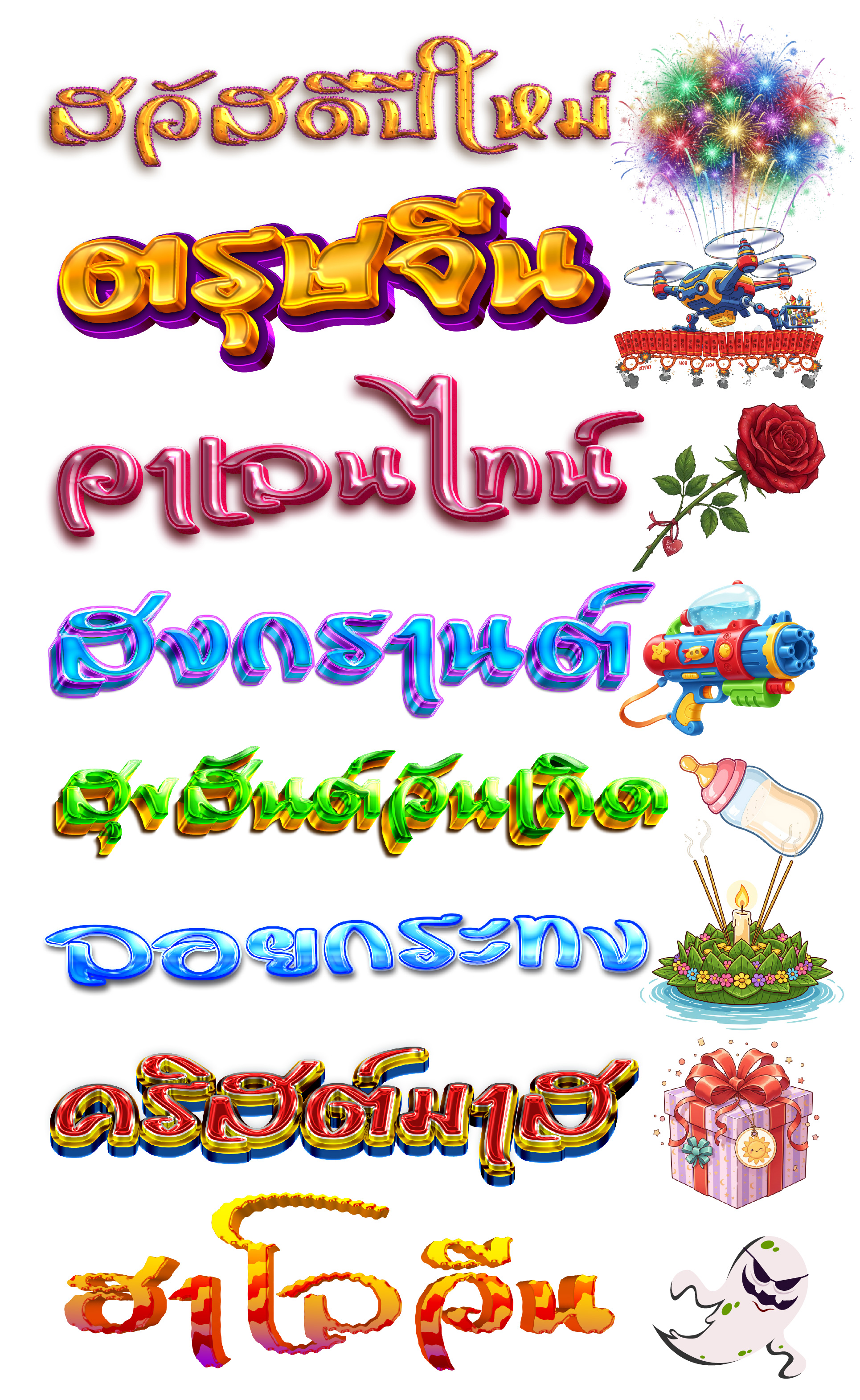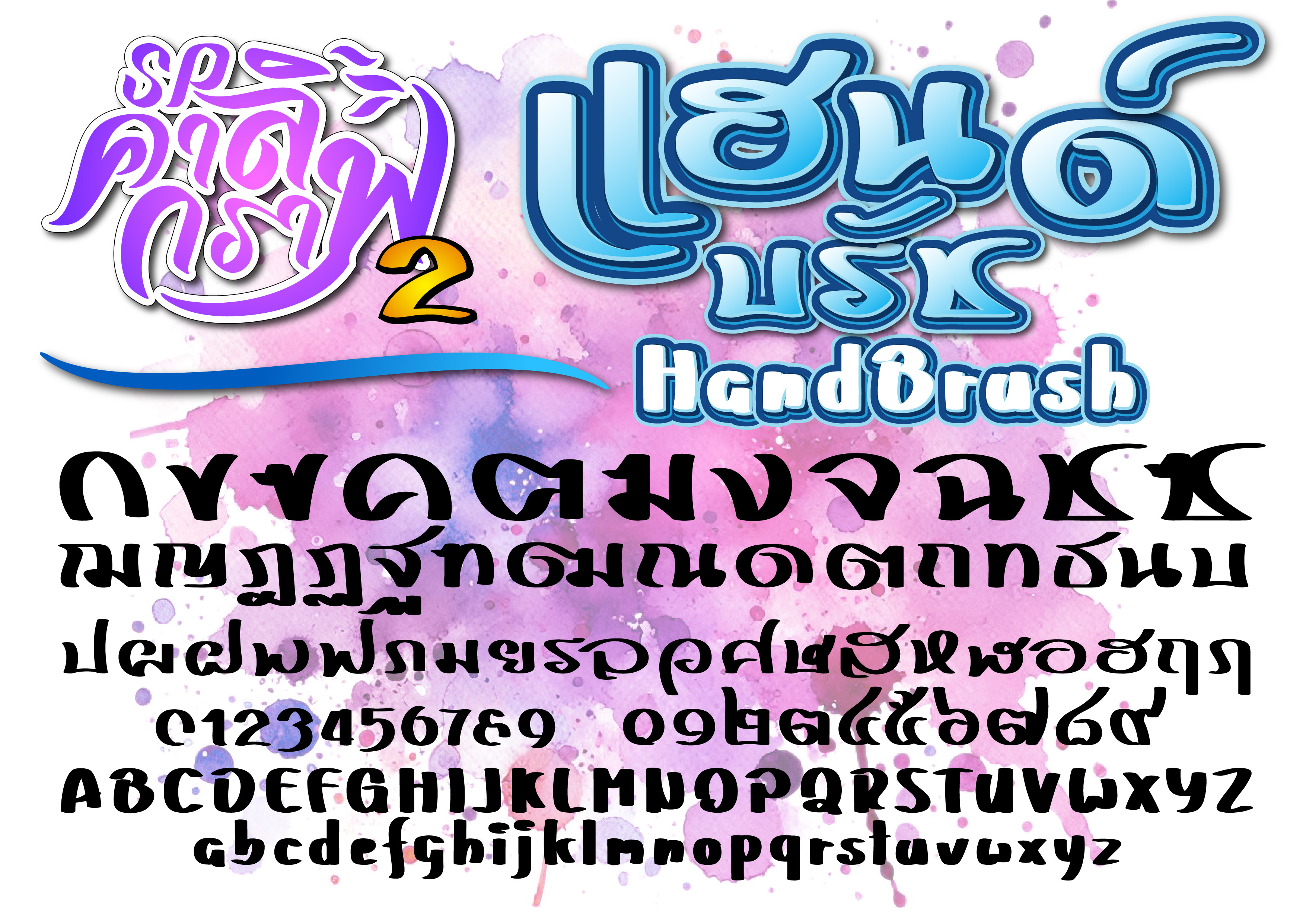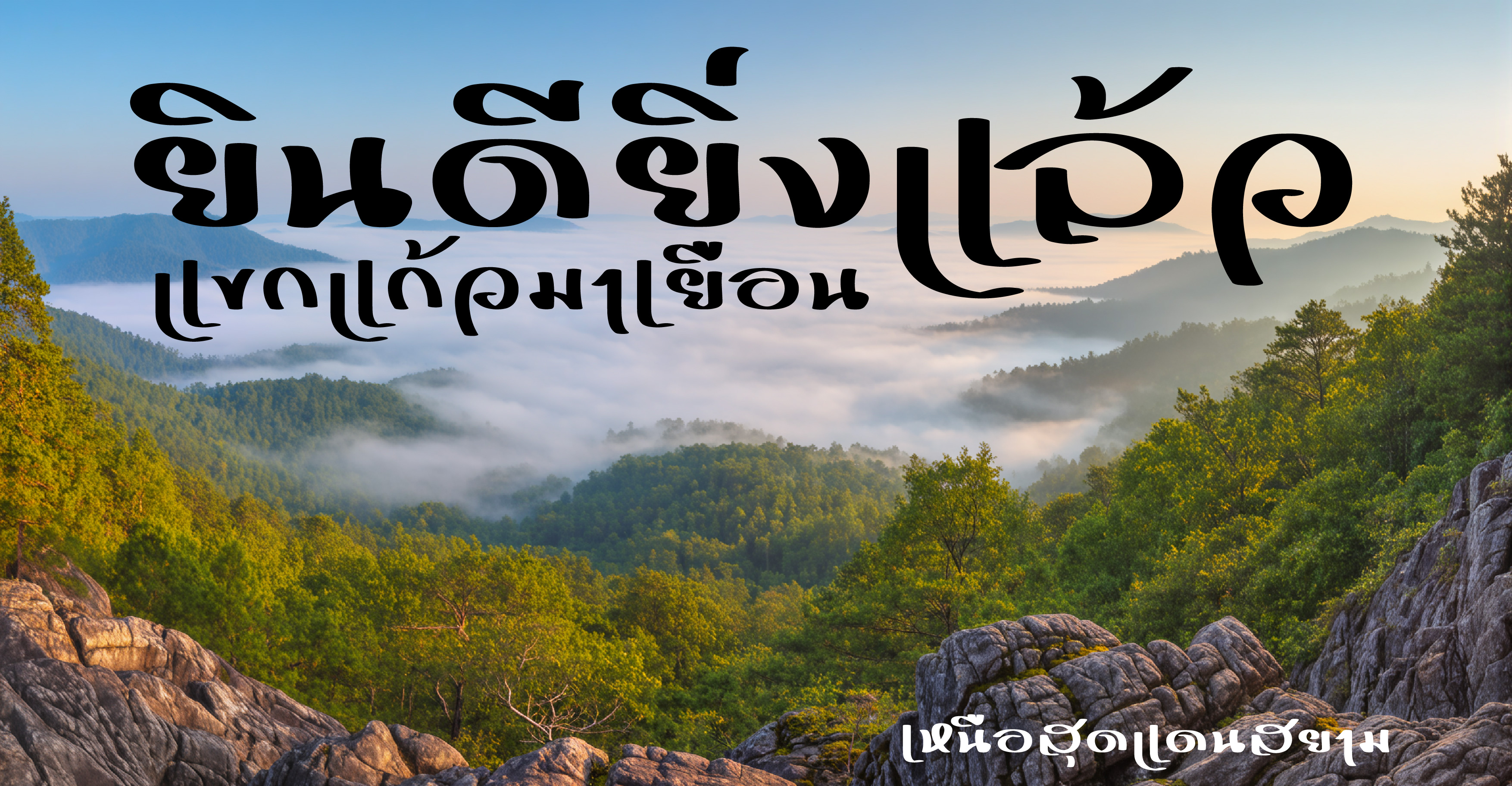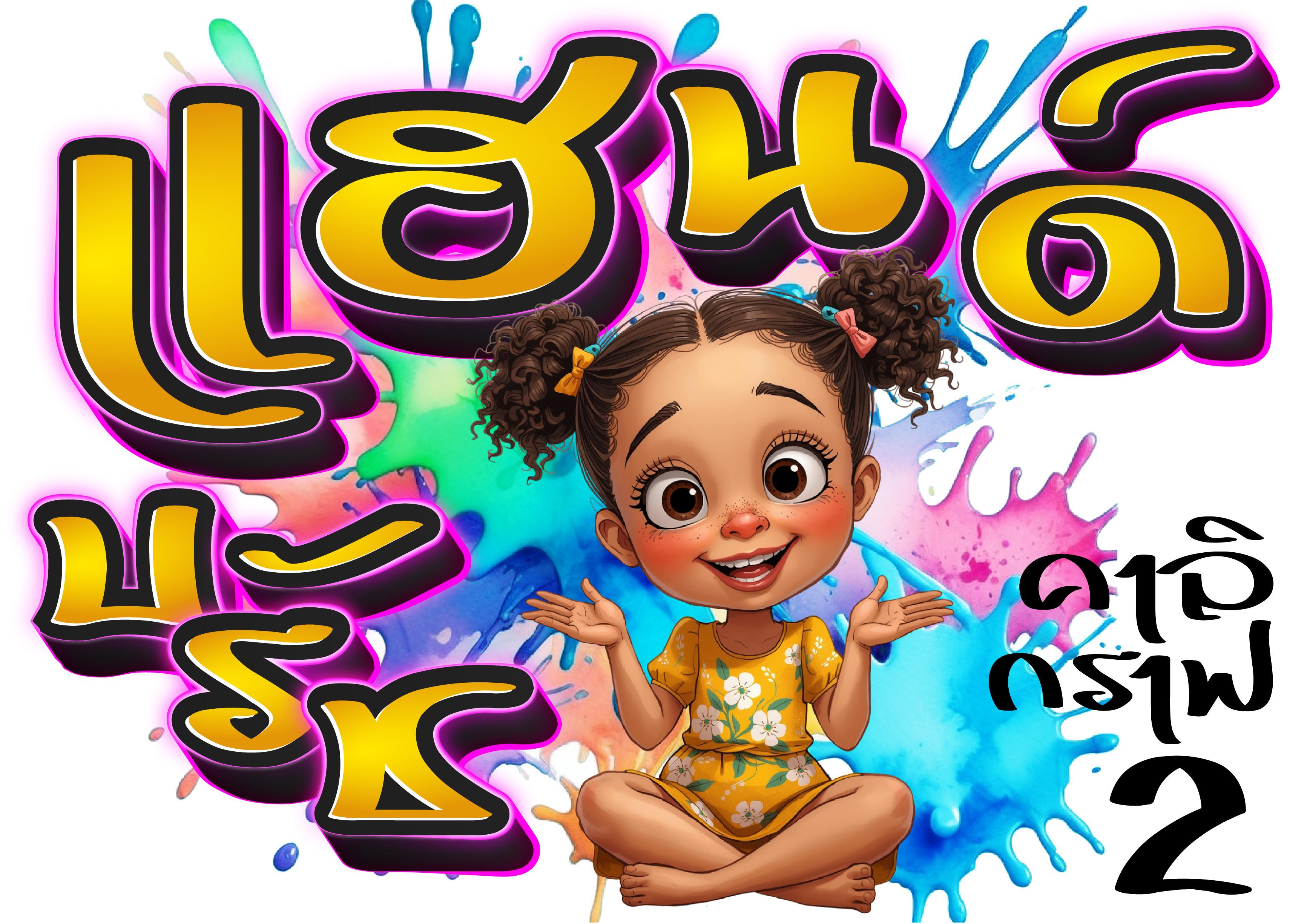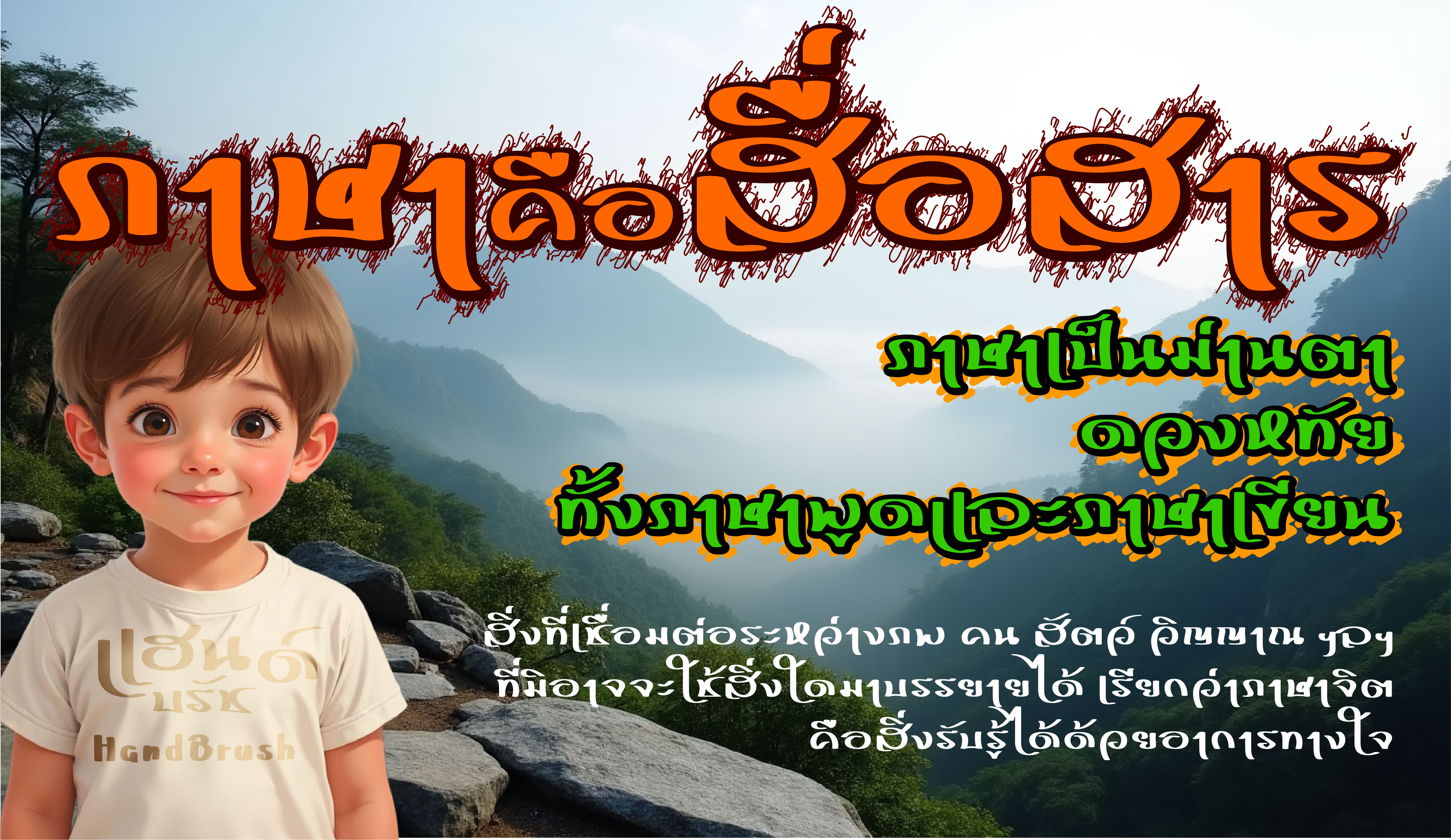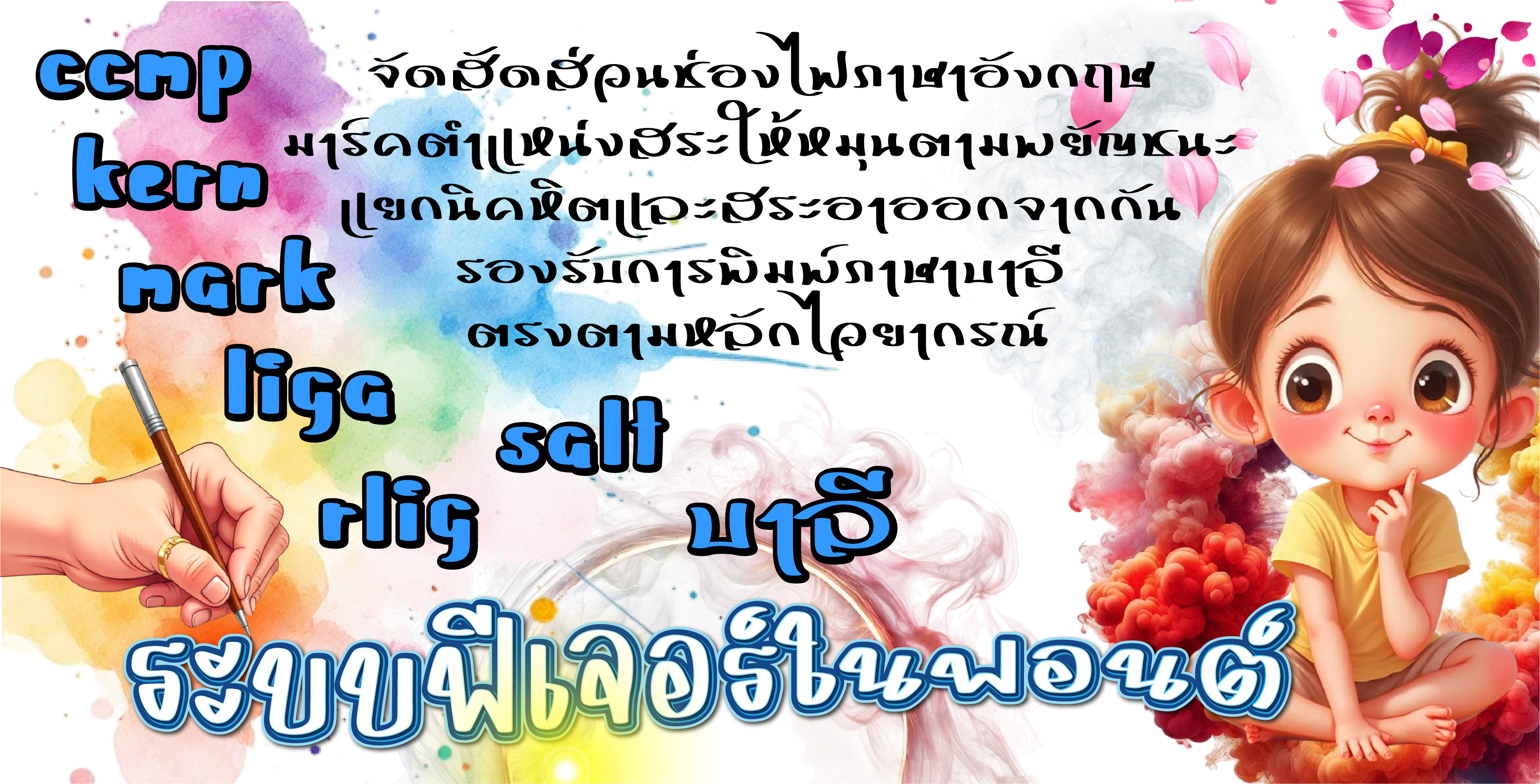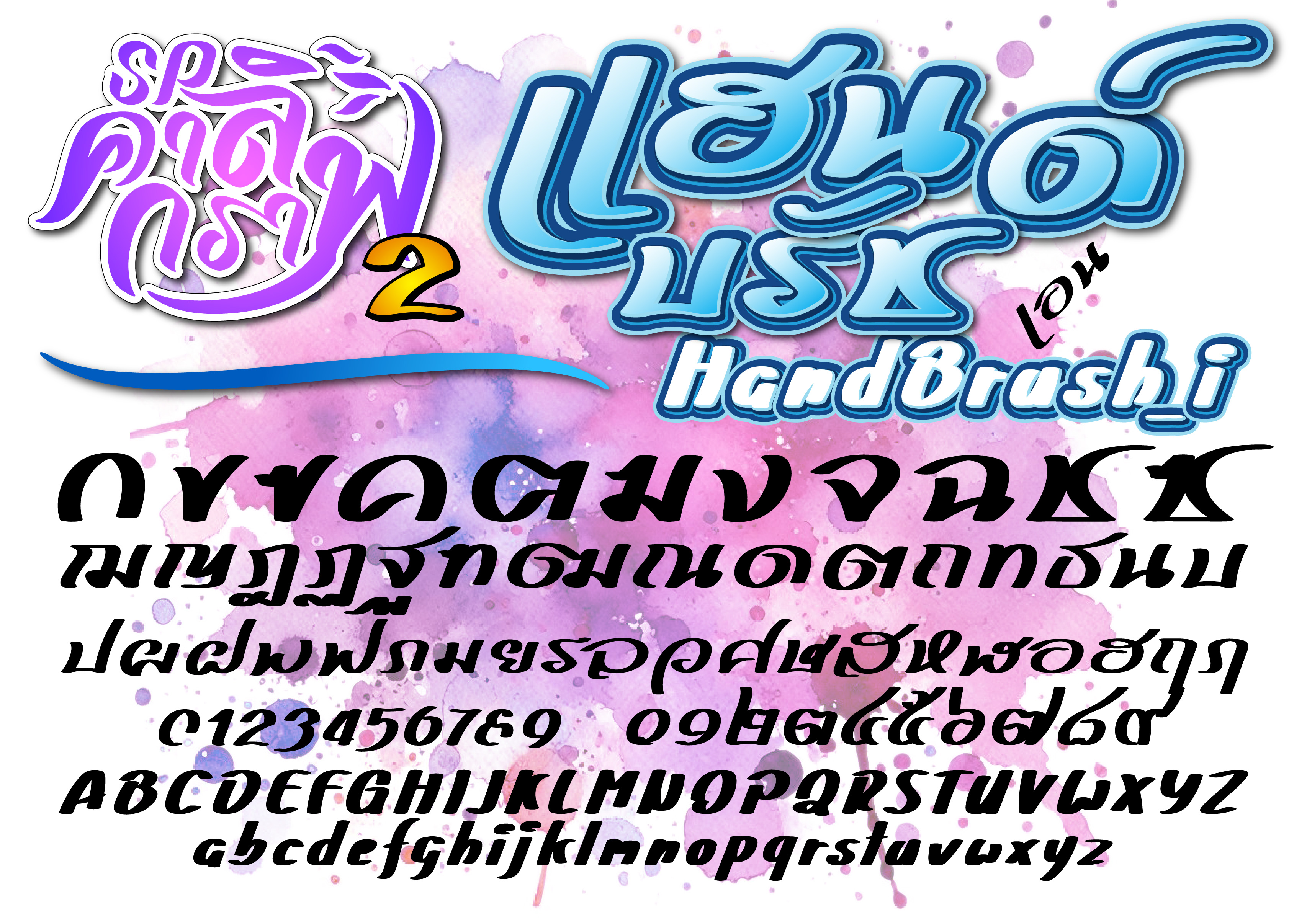
ฟอนต์ลายมือ เย็นตาโฟ (LMF Yentafo )
คาลิกราฟ 2 (ฟีเจอร์มาร์ค)
SP_HandBrush แฮนด์บรัช
ฟลอร่า (PG Flora)
ฟอนต์รับรัก (TCS4RubRuk)
ฟอนต์ "เดย์แอนไนท์" (TTA Day and Night)✨
ฟอนต์ลายมือสุดคิ้วท์ที่ใช้ได้ดีทั้งกลางวันและกลางคืน จะจดโน้ต ทำสรุป หรือแต่งรูปก็น่ารักไปหมด
​จัดเต็ม 2 น้ำหนัก:
Light: เส้นบางเบา ดูสะอาดตา เหมาะกับงานสายมินิมอล
Regular: เส้นมาตรฐาน อ่านง่าย ชัดเจน